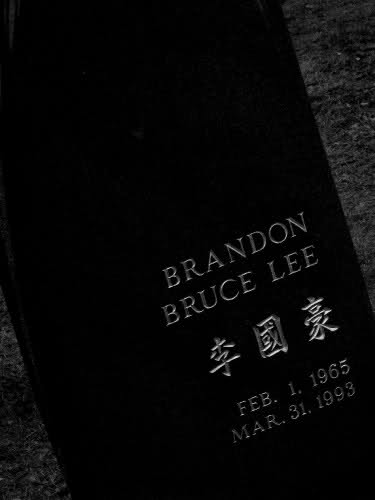
Tombstone-Spotter
Ich kann leider nicht perfekt Ausländisch … aber zumindest sichtbar machen konnte ich es.
Nette Steinchen ... Schade dass man von dem Engel nicht mehr sieht :D
Graublau Sans mit Titling Feature:
weitere reduzierte Grabsteine:
und in den Strawberry Fields John Lennon :
… wie solche Feinheiten möglich sind …
Ja, wunderschön dreidimensional ausgearbeitet und alles händisch und ohne Rechner. Ich habe mich auch gefragt, wie ein Steinmetz so eine perfekte Kugel (Grabstein Albert A. Volk) hinbekommt.